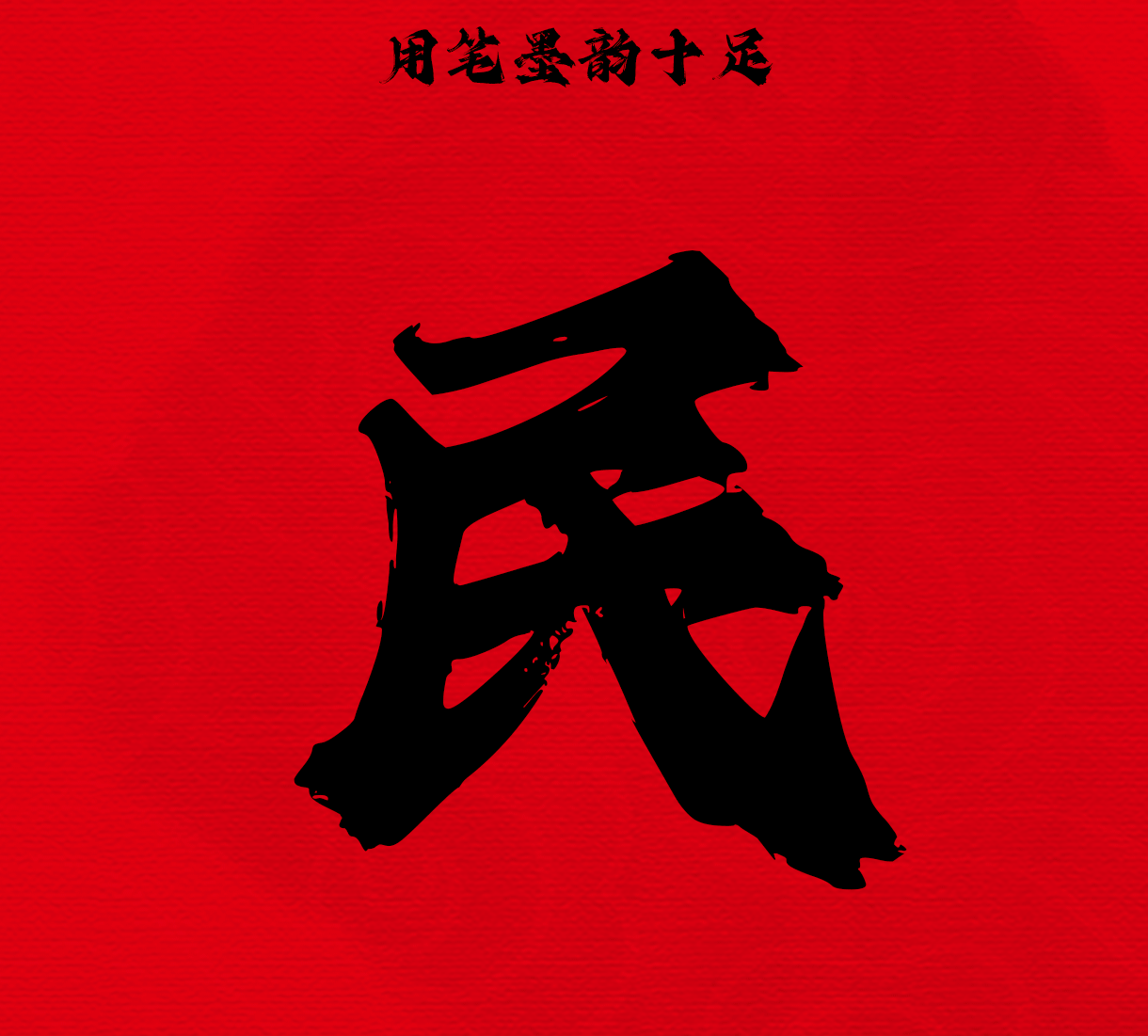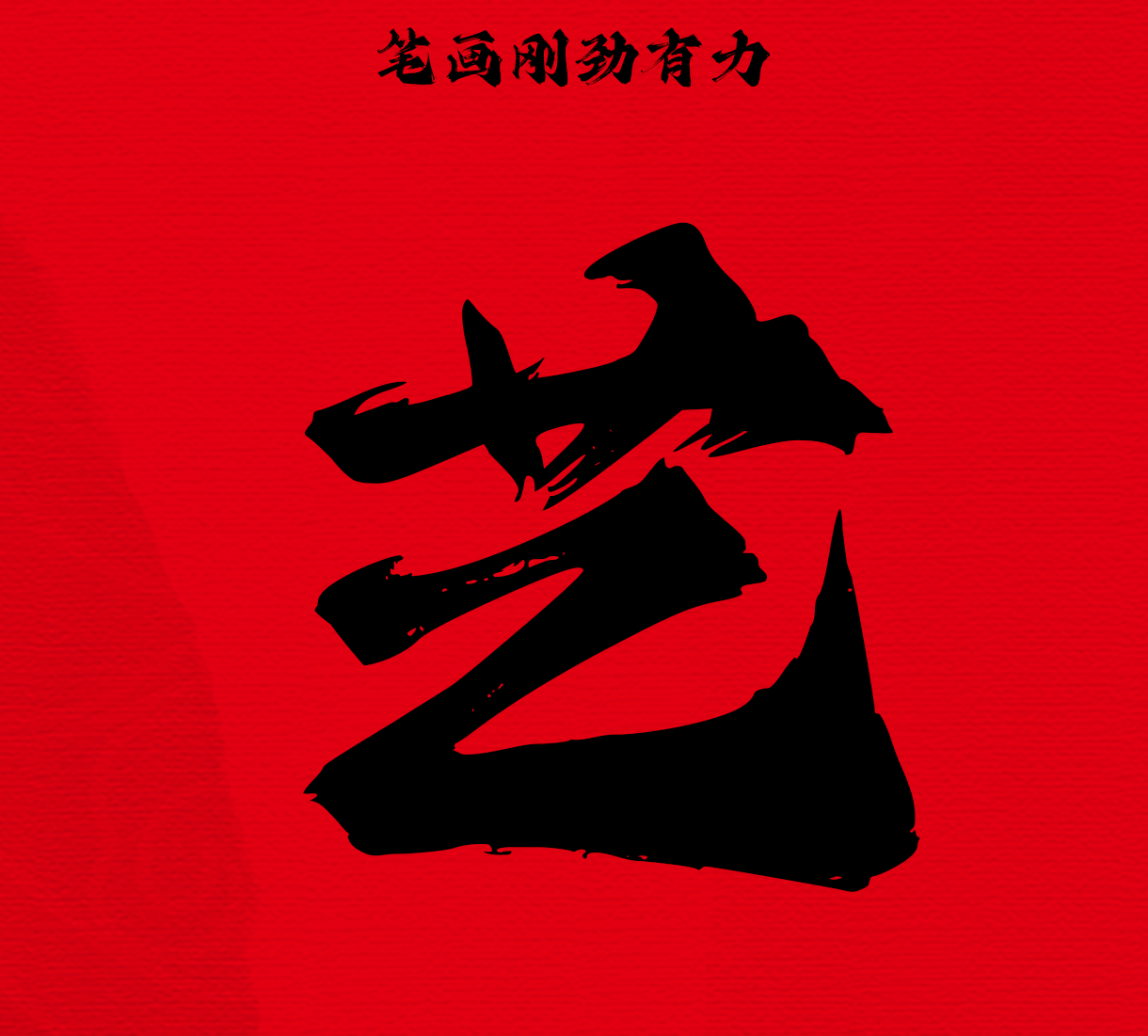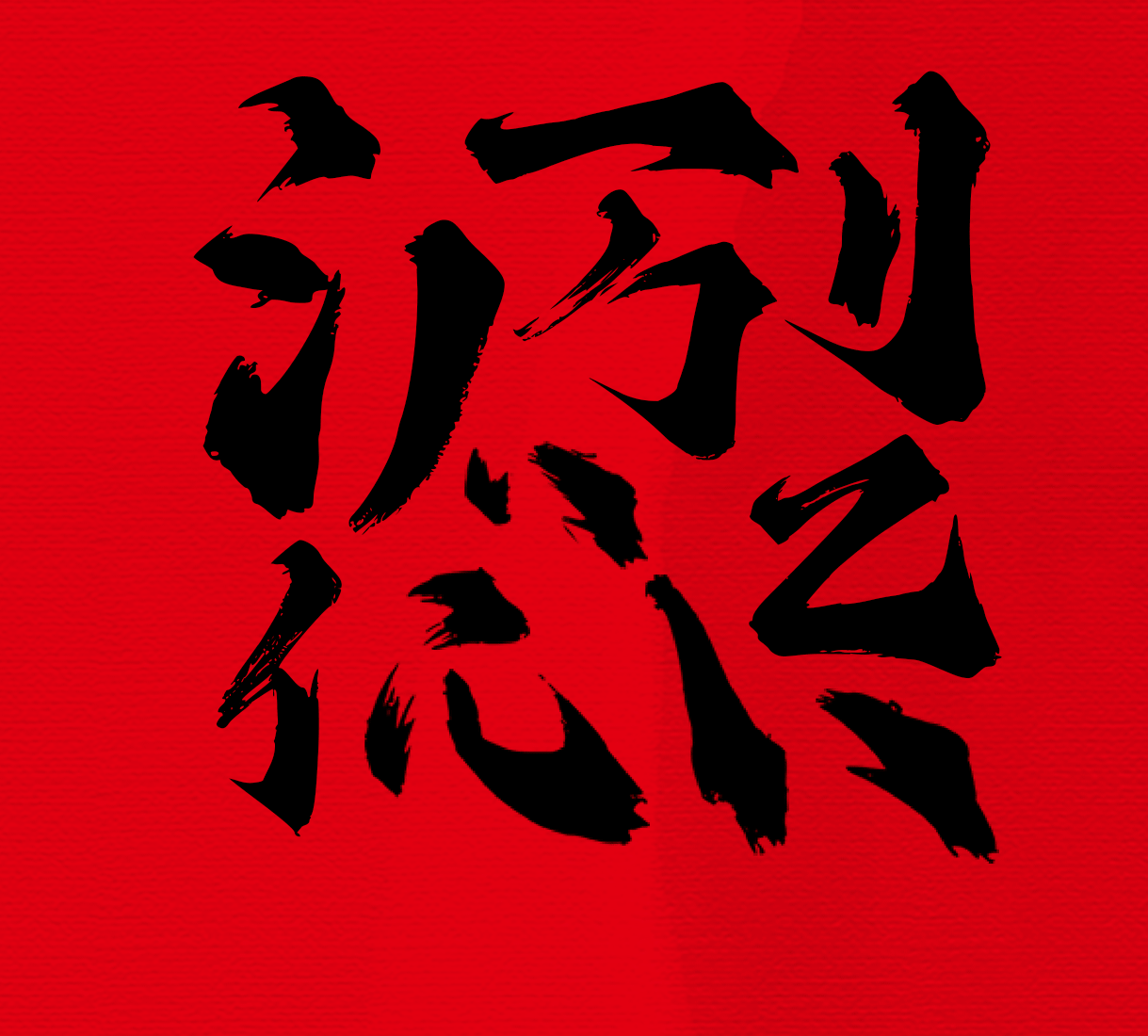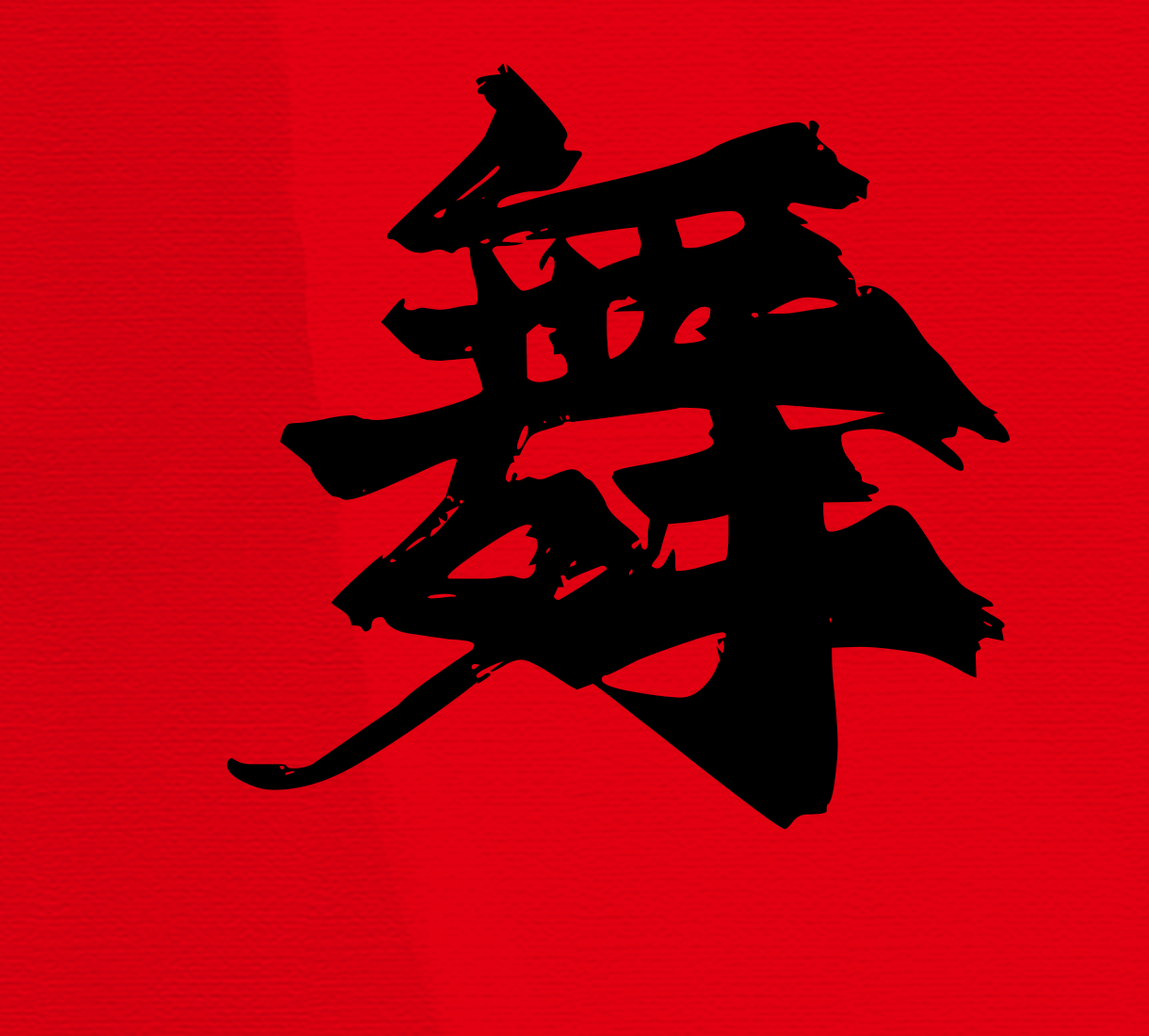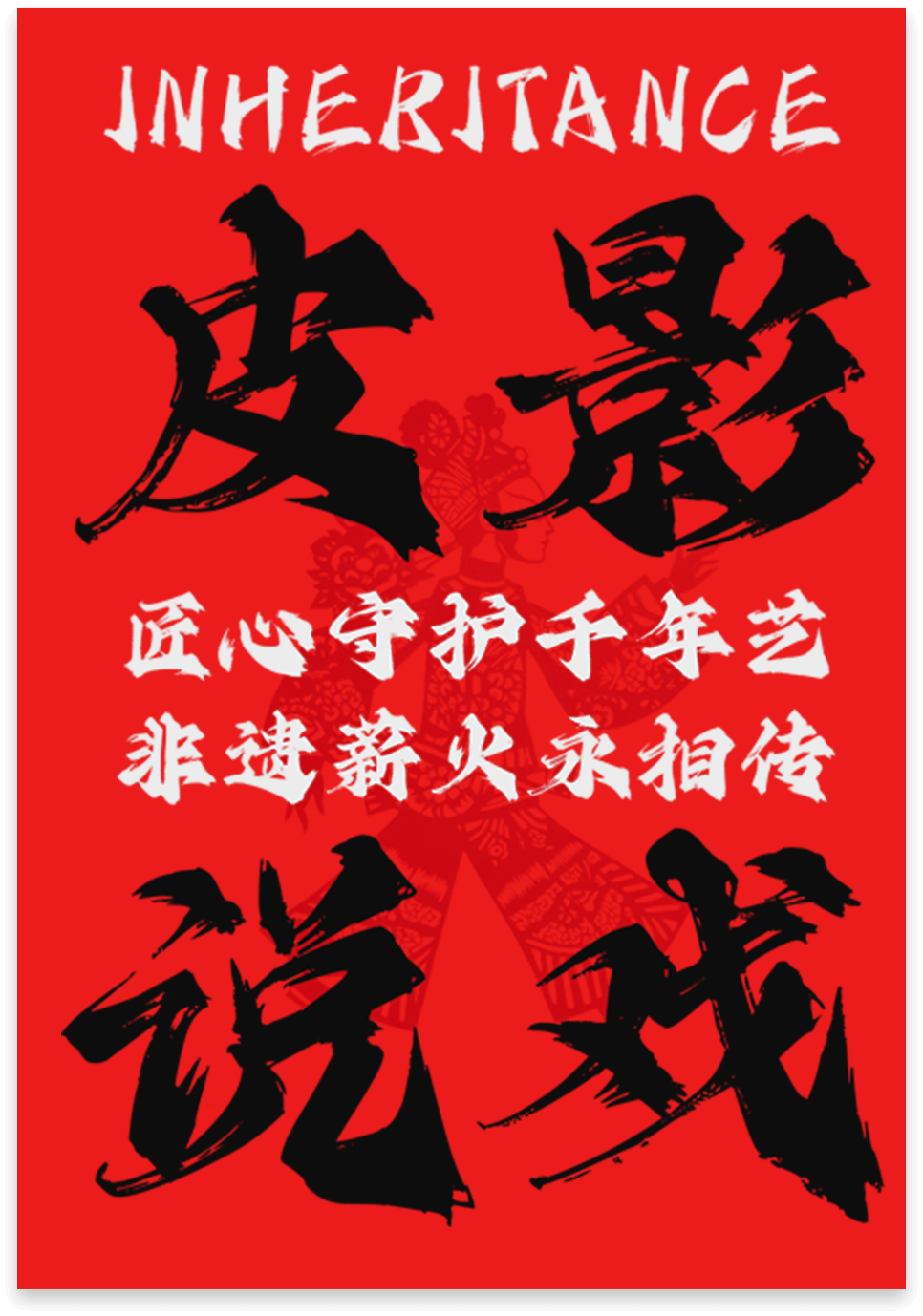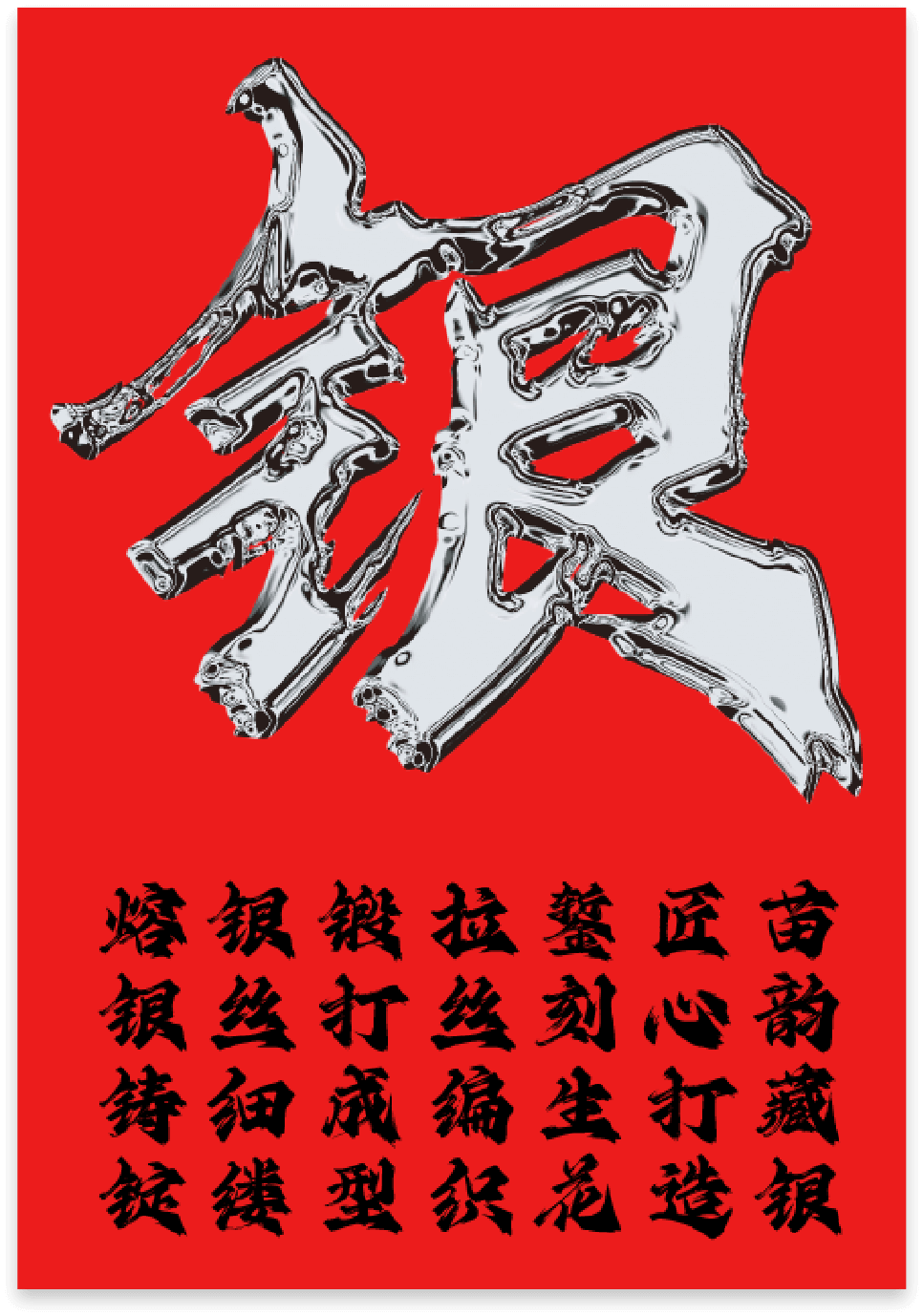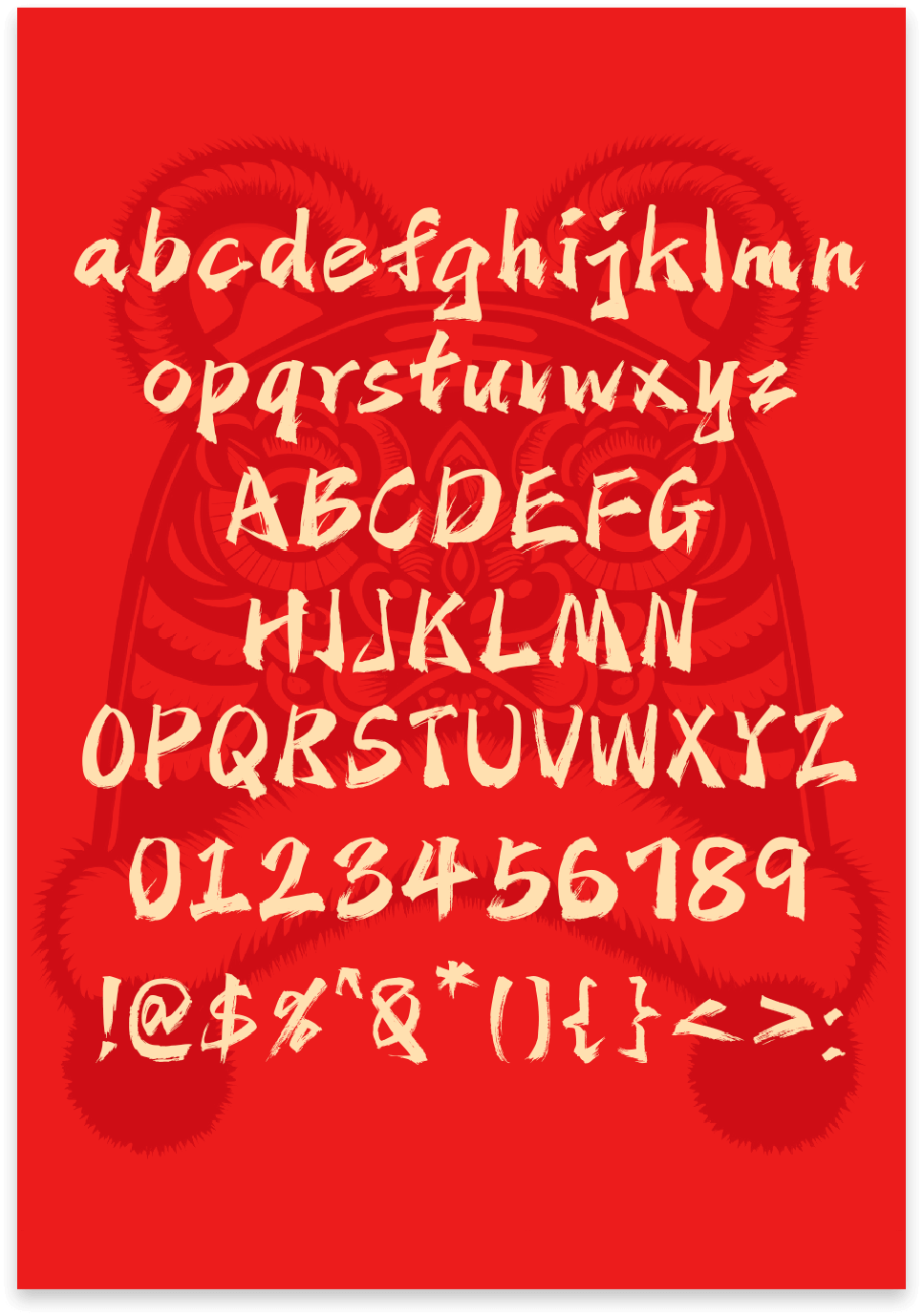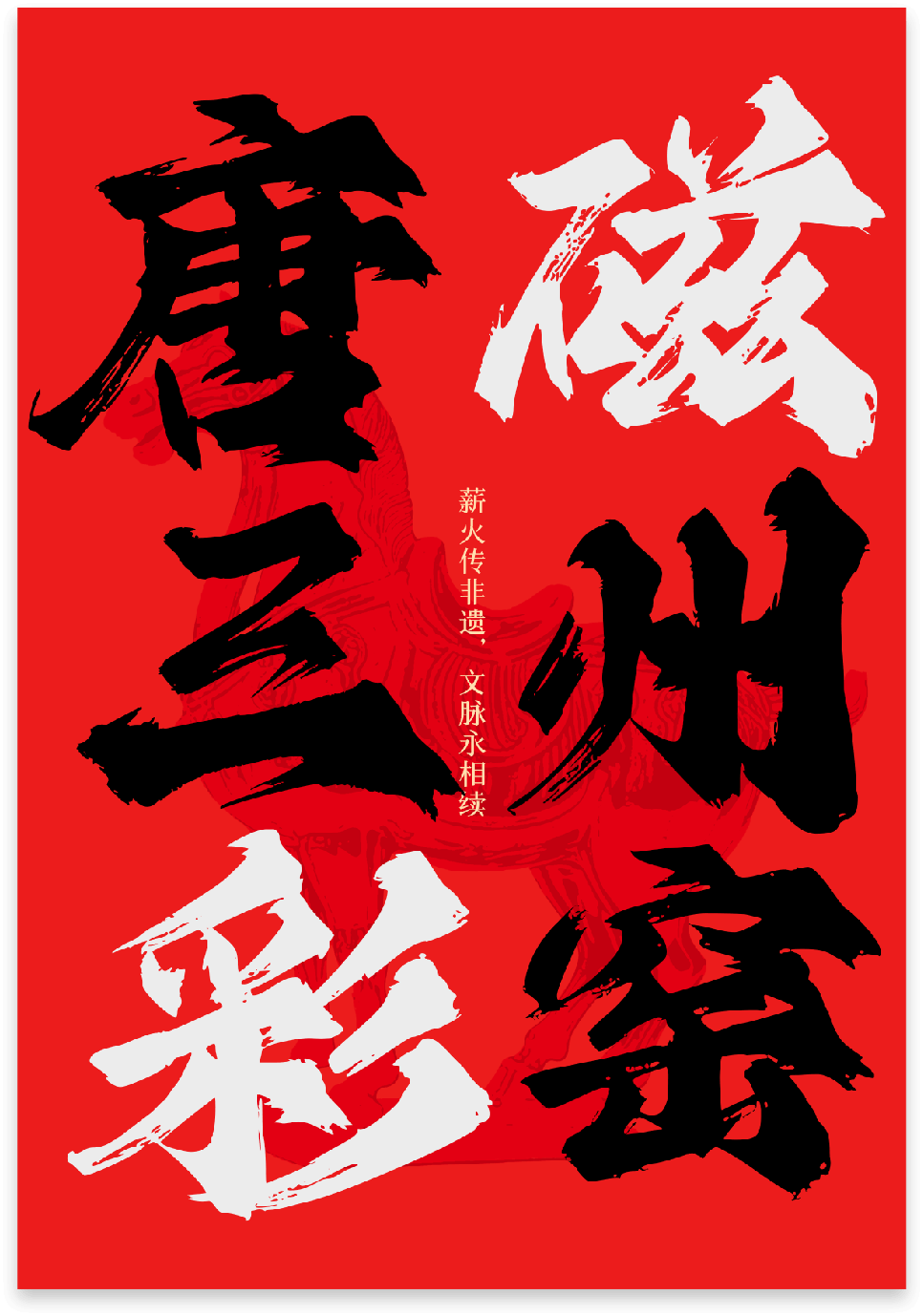
字魂北京民艺非遗研究院体
染缸里荡漾的蓝靛,剪纸老人手中的红纸,皮影戏班传唱的古老唱腔……
非遗,既是凝固的历史,也是活着的文明
北京民艺非遗研究院,立于传统根基搭建古今桥梁,汇集有180+非遗门类及千位非遗大师
让文化遗产从“纸上名录”走向人间烟火
凝练「承古立新」的匠心智慧
字魂与其携手推出定制字体——「字魂北京民艺非遗研究院体」
共同向传统文化的传承与创新致敬
以艺载道 字承匠心
在数字化浪潮下,如何建立统一、强辨识度的视觉语言
承载非遗的深厚底蕴与无穷活力
使其服务于其广泛的传播、研究、合作与产业转化?
一款承载非遗灵魂、兼具传统韵味与现代适用性的定制字体
成为了北京民艺非遗研究院
深化品牌内涵、拓展传播边界、赋能产业合作的重要工具
• 源于文房四宝承载的毛笔书写,保留了自然笔锋变化与墨韵效果。笔画呈现古朴气质与传统韵味,与非遗文化传统根基相呼应。
• 象征着研究院在“正本清源”工作中的严谨态度、非遗传承人坚守技艺的执着信念,以及非遗文化本身历经沧桑而生生不息的强大生命力,传递出坚定的文化自信。
• 结构灵动洒脱
呼应研究院“搭建桥梁”、推动非遗“时尚化、经济化、产业化”的开放态度,象征非遗不是僵化的标本,而是在尊重本源基础上的活态传承与创新发展。
整体字体设计在严谨的法度中蕴含着自由的表达,这正是民艺非遗传承理念的核心——在敬畏中创新,在传承中发展,古为今用、继往开来,是非遗精神与手书美学的深度融合。
民俗之美 以字传魂
非遗定制 承古立新
字魂北京民艺非遗研究院体
是为北京民艺非遗研究院打造的独特视觉资产
这款字体既保留了传统技艺的温度
也承载着“连接传统保护与当代创新”的品牌价值观
以刚劲笔锋构筑文化自信,借灵动结构抒写继往开来
让研究院“承古立新”的使命在每一处笔触转折中具象生长
字体定制,不仅有关设计造型
更有关文化共识的共建、核心理念的共鸣
当精心设计的视觉语言
服务于机构从文化研究、产业合作到大众传播的全场景应用时
品牌的每一次发声
都将更具辨识度与感染力,成为触动人心的更强音